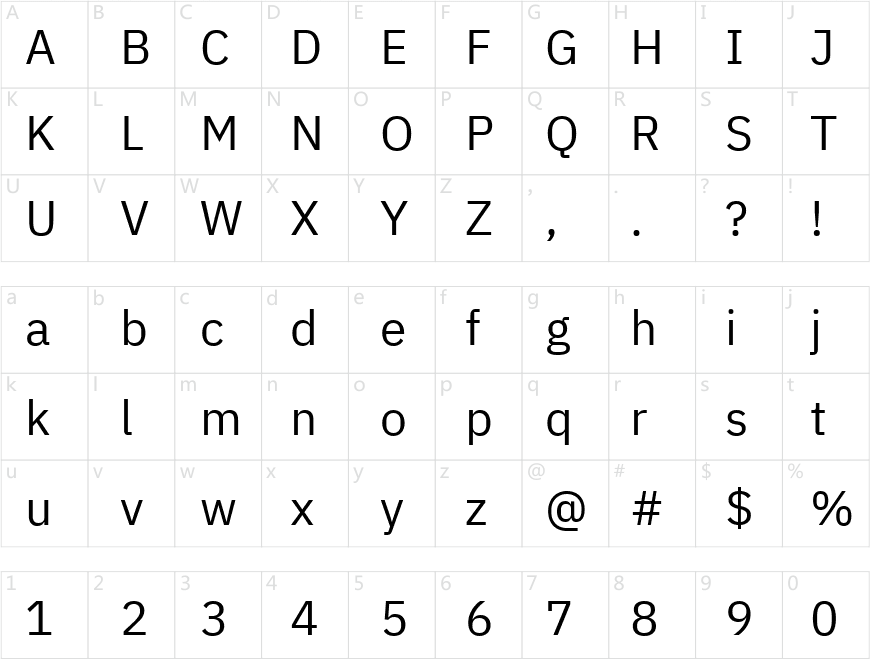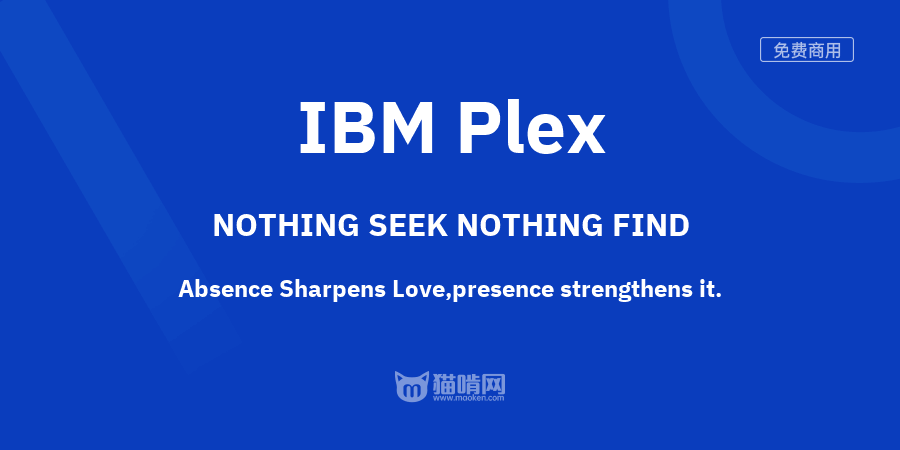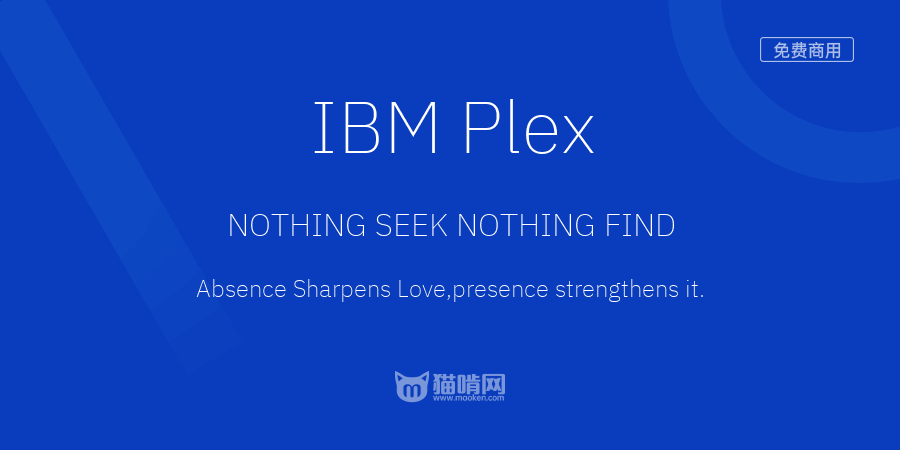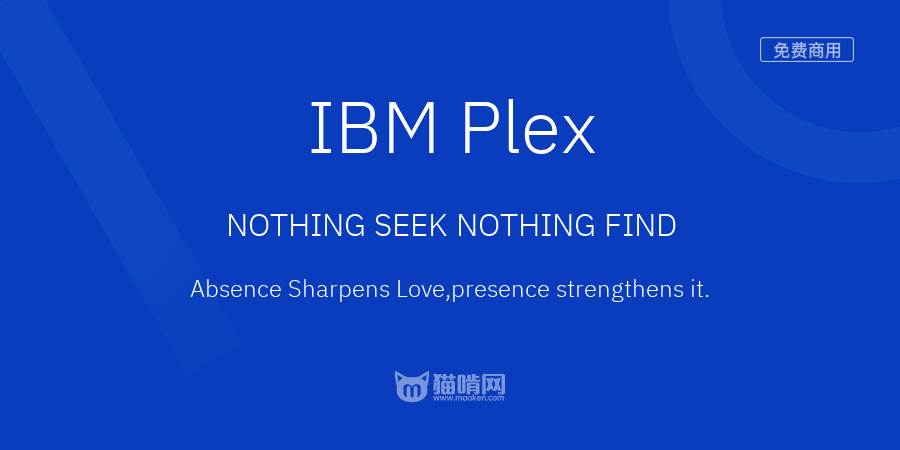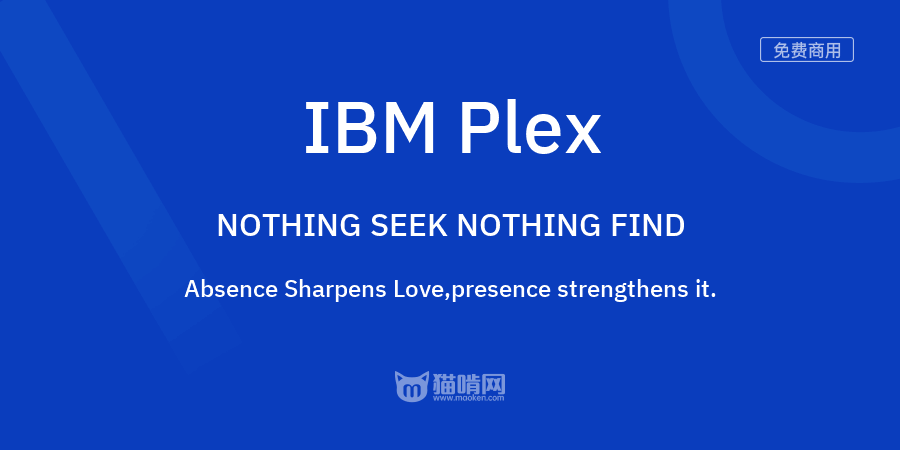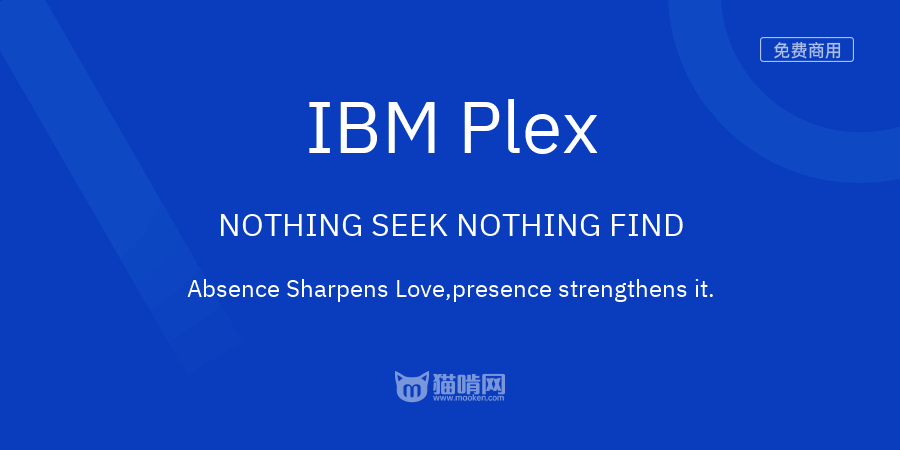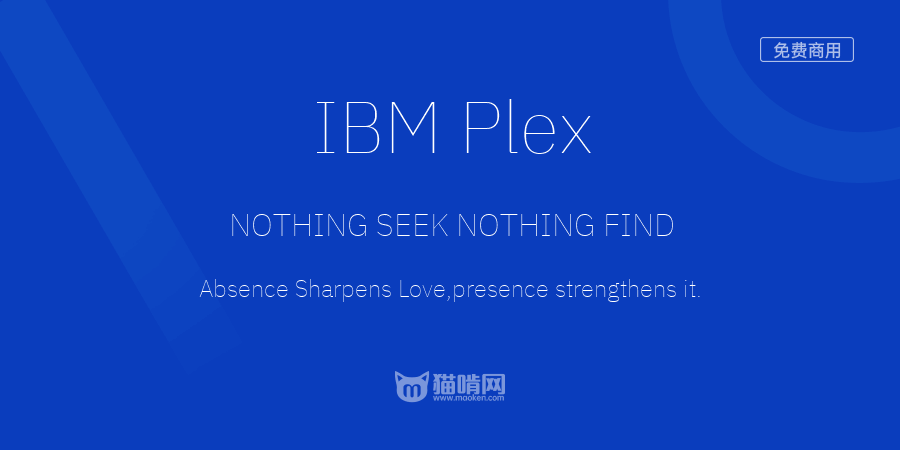
IBM Plex
IBM Plex是IBM的新字体。它是全球性的,它是多功能的,它是独特的IBM公司字体。计算机巨头IBM发布的的开源字体,用于替代Helvetica。 IBM Plex 的字体是开放源码的,任何人都可以下载使用,而Helvetica需要支付许可费才能使用。
IBM Plex Family 由三大字体类型组成:Sans-serif(无衬线体)、Serif(衬线体)和 Mono(等宽字体),相信熟悉英文字型的朋友对于这三种字体类型一定不陌生,每种类别有八种不同的字重:Thin、ExtraLight、Light、Text、Regular、Medium、Bold、SemiBold,也有为斜体设计的 Italic 系列。
这是IBM Plex Sans,还有IBM Plex Serif,也开源